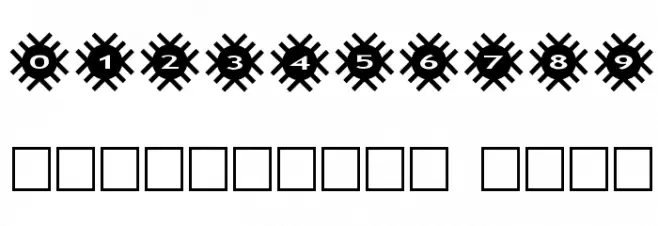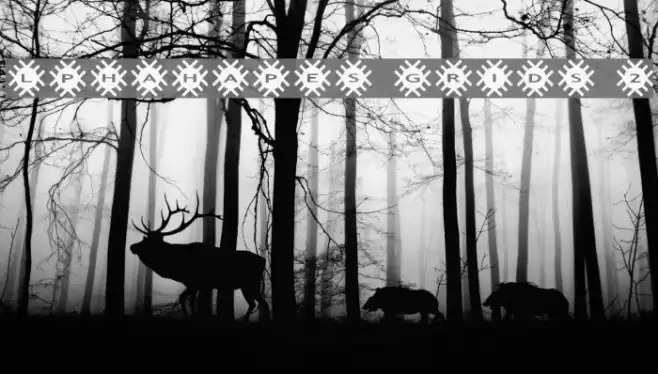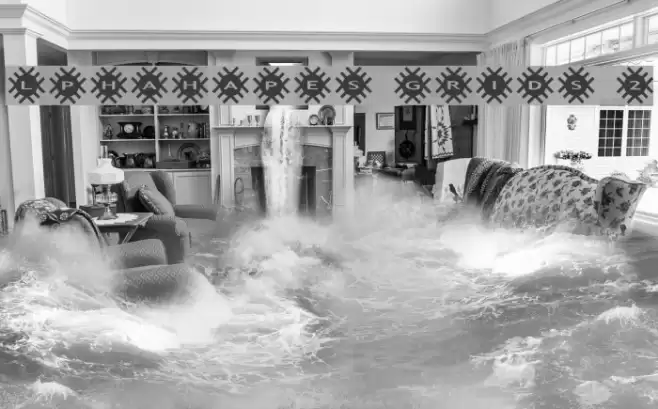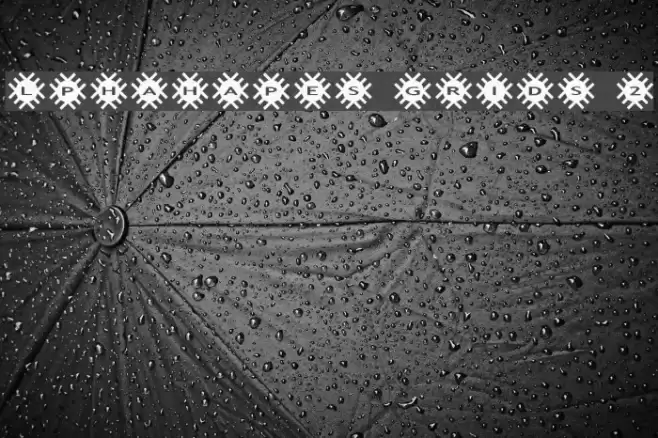
AlphaShapes grids 2 Font
| Общий стиль | Modern, Artistic |
| Область применения | Logos, Headlines, Posters |
| Рекомендуемые проекты | Ideal for creative projects such as posters, album covers, or branding materials where a distinctive and artistic look is desired. |